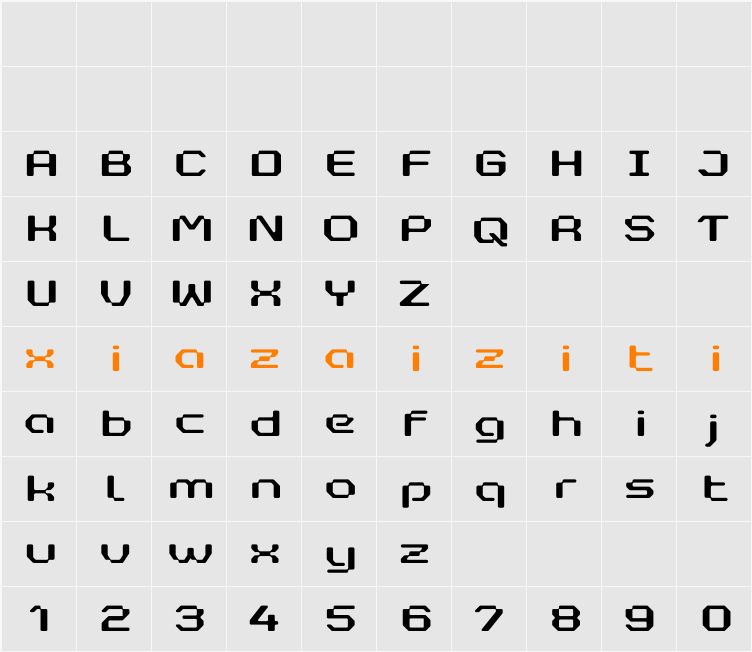
Retro Pixel
Retro Pixel,这款字体结构工整、笔画清晰,兼顾美观与易读性,适用于标题、正文、海报、包装、LOGO 等多种场景。字形优雅稳定,风格百搭耐看,适配日常排版与创意设计,让文字呈现更舒适、更具质感。Retro Pixel一笔一画,皆是细节,以均衡的比例、流畅的线条打造舒适视觉体验,字形端正大气,风格简约现代。无论是商业设计、品牌宣传还是日常排版,都能轻松驾驭,让文字更有格调与力量。Retro Pixel字体下载。